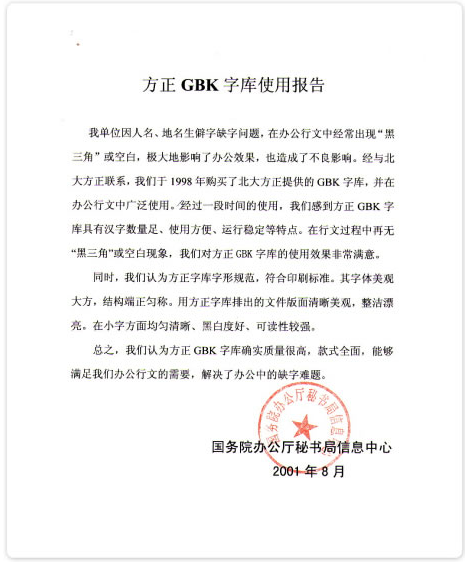
按照《党政机关公文格式》国家标准(GB/T 9704-2012)的规定:
公文的发文机关标志和公文标题必须使用小标宋
公文的发文字号、主送机关、抄送机关和公文正文等必须使用仿宋
公文的密级、保密期限和紧急程度必须使用黑体
公文的签发人和文中结构层次序的第二层必须使用楷体
《方正兰亭GBK办公字库》是北大方正电子有限公司开发的标准TrueType中文字库,采用GBK编码,共收录汉字21003字,包含8款GBK字库(黑体、宋体、仿宋、楷体、超粗黑、隶书、小标宋、魏碑)可运行于Windows、Linux等系统中,并能满足在办公软件中对中文字库的要求。主要特点如下:
•    支持GBK编码标准:方正GBK办公字库严格按照国家颁布的GBK编码标准制定,共收录了21003个汉字,完全兼容GB2312-80标准,支持国际标准ISO/IEC10646-1和国家标准GB13000-1中的全部中日韩汉字,并包含了BIG5编码中的所有汉字。可以极大的减少发生冷僻字的情况,可以让党政机关之间进行电子文件共享交流时,实现文件的完美、准确、原版的显示效果,满足政府办公对用字的需求。
•    字形美观:方正GBK办公字库由字体设计专家设计,字形端庄美观,符合国家颁布的字形规范,并首家通过由国家新闻出版署、国家语言文字工作委员会、全国印刷字体工作委员会联合主持的GBK字库鉴定。方正公文仿宋字体比普通仿宋体适当加粗,使公文更加清晰易读。
•    通用性、兼容性强:方正GBK办公字库完全符合国家用字规范和印刷标准,支持多种输出设备和输出方式。
•    安全可靠:方正四十多年的字库开发经验,及众多党政机关的应用实践,确保方正字库的安全稳定运行。
作为方正GBK字库最早的用户之一,国务院办公厅自1998年就开始购买和使用了方正GBK字库,解决了由于办公过程遇到无法输入的生僻字而出现“黑三角”或空白的问题,通过使用,国务院办公厅对方正GBK字库的使用效果非常满意。新华社也早于2000年1月1日起采用GBK编码发新闻稿,《人民日报》及代印点同年全面改用方正GBK字库。